คู่มือนักพัฒนาเกี่ยวกับการใช้ Supreme Font ในแอพมือถือ
เผยแพร่แล้ว: 2022-10-04แบบอักษรที่เหมาะสมคือสิ่งที่คุณต้องการเพื่อให้เว็บไซต์ของคุณประสบความสำเร็จอย่างมาก คุณเคยผ่านไซต์ที่ใช้แบบอักษรผิดและทำให้คุณเปลี่ยนไปใช้ไซต์อื่นที่ใช้แบบอักษรอย่างถูกต้องในทันทีหรือไม่? มันเกิดขึ้นเมื่อคุณไม่มองหาสิ่งเล็กน้อยที่สร้างความแตกต่างอย่างมากในภายหลัง
ฉันมาที่นี่เพื่อพูดคุยสั้น ๆ เกี่ยวกับแบบอักษรที่ชื่นชอบมากที่สุดตัวหนึ่ง กล่าวคือ แบบอักษรสูงสุดกำลังได้รับการยอมรับ โดยเฉพาะสำหรับไซต์บนมือถือ มาพูดถึงว่าทำไมมันถึงกลายเป็นทอล์คออฟเดอะทาวน์สำหรับนักพัฒนาหรือว่ามีอะไรพิเศษบ้าง
Supreme Font คืออะไร?
Supreme เป็นหนึ่งในแบรนด์ที่ใหญ่ที่สุดในนิวยอร์ก หลังจากที่เห็นโลโก้แล้วก็ต้องสงสัยว่าพวกเขาใช้ฟอนต์แบบอื่นที่ไม่เคยใช้มาก่อน อย่างไรก็ตาม มันตรงกันข้ามโดยสิ้นเชิง แบบอักษรที่ใช้บนโลโก้ของ Supreme เป็นรุ่นของ Future ที่เผยแพร่เมื่อหลายปีก่อนและถูกใช้ในสถานที่ต่างๆ มากมาย
ตั้งแต่สเก็ตบอร์ดไปจนถึงเสื้อผ้า แบรนด์นี้ผลิตเครื่องประดับอื่นๆ แทบทุกอย่าง โลโก้ของพวกเขาได้รับความสนใจอย่างมากด้วยเหตุผลที่ดีทั้งหมด แม้จะใช้ตัวแปร Futura แบบเฉียงหนา แต่พวกเขาก็เลือกแบบอักษรที่เหมาะกับบริบท
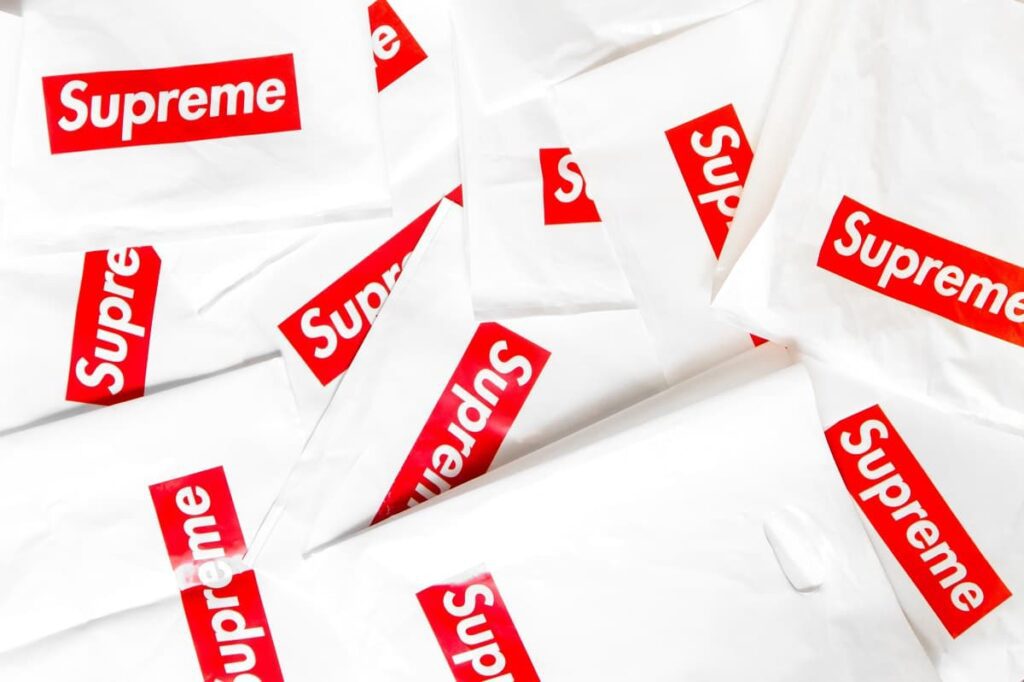
ทำไมต้องใช้ Supreme Font ในแอพมือถือ?
คุณรู้หรือไม่ว่าแบบอักษรสูงสุดนั้นเพิ่มขึ้นอย่างรวดเร็วเมื่อเวลาผ่านไปหลังจากใช้บนโลโก้ บางคนอาจสงสัยว่าทำไมเราควรเลือกใช้แบบอักษรนี้ โดยเฉพาะในแอปบนอุปกรณ์เคลื่อนที่ หรือเราได้ประโยชน์อะไรจากการใช้แบบอักษรนี้ มาพูดถึงบางสิ่งที่บรรยายว่าทำไมฟอนต์นี้ถึงเป็นทอล์คออฟเดอะทาวน์ และคุณต้องลงมือสำหรับโปรเจ็กต์ในอนาคตของคุณ
มันช่วยเพิ่มความสามารถในการอ่าน
สำหรับนักพัฒนาหรือนักออกแบบ ความสามารถในการอ่านเป็นประเด็นหลัก เพราะหากผู้อ่านไม่สามารถเข้าใจมุมมองของคุณได้ ไซต์ของคุณก็ล้มเหลวอย่างใหญ่หลวง แบบอักษร Supreme หรือแบบอักษร Futura ขึ้นชื่อเรื่องคะแนนความสามารถในการอ่าน ความหนาคงที่ของตัวอักษรแต่ละตัวและการออกแบบที่เรียบง่ายทำให้เข้าใจบริบทได้ง่าย
ไม่เพียงแต่ Futura เท่านั้น แต่ทุกเวอร์ชันทำให้ไซต์เข้าใจได้ง่าย ตัวแปร Supreme ใช้ได้ดีสำหรับจุดประสงค์ในการโฆษณาเนื่องจากคุณสมบัติความเข้าใจนี้
เหมาะสำหรับแบรนด์
หากคุณกำลังใช้งานแบรนด์ คุณต้องใช้แบบอักษรที่เหมาะสมเพื่อทำให้ข้อความดูคมชัด เพื่อให้ผู้คนสามารถรู้ว่าแบรนด์นี้เกี่ยวกับอะไรและให้บริการอะไรแก่ลูกค้า เมื่อพูดถึงการสร้างอำนาจแบรนด์ การเลือกแบบอักษรที่เหมาะสมเป็นสิ่งสำคัญ Futura เวอร์ชันนี้มีเส้นขีดบางๆ ที่ทำให้ข้อความดูชัดเจนยิ่งขึ้นด้วยขอบที่แหลมคม นั่นเป็นเหตุผลที่ผู้คนเลือกมันอย่างมากด้วยเหตุนี้
ใช้โดยแบรนด์ใหญ่
คุณรู้หรือไม่ว่าแบรนด์ชั้นนำมากมายใช้ฟอนต์ Futura รุ่นต่างๆ มาหลายปีนี้ ซึ่งได้เพิ่มความโดดเด่นของฟอนต์นี้ ตอนนี้ผู้คนไม่คิดว่าเป็นวินาทีก่อนใช้งานแบบอักษรนี้ ทุกคนเคยใช้โลโก้นี้ในโลโก้ของตน ตั้งแต่ Dominos ไปจนถึง Nike ไปจนถึงแบรนด์อื่นๆ และที่เหลือคือประวัติศาสตร์ กล่าวโดยย่อ ฟอนต์ Futura ไม่ได้เชื่อมโยงกับ Supreme เท่านั้น เนื่องจากมีชื่อที่มีชื่อเสียงอื่นๆ ที่เกี่ยวข้องด้วย
แบบอักษรอเนกประสงค์
อะไรจะดีไปกว่าการใช้แบบอักษรอเนกประสงค์บนเว็บไซต์ของคุณที่มีลายเส้นและการออกแบบแบบอักษรที่แตกต่างกัน นี่คือสิ่งที่ดีที่สุด Futura เวอร์ชันดัดแปลงนี้ใช้งานได้หลากหลายและปรับให้เข้ากับการออกแบบประเภทต่างๆ ได้ค่อนข้างดี สำหรับแอพมือถือต่างๆ คุณสามารถทดลองใช้งานได้อย่างง่ายดายโดยไม่ต้องสงสัย
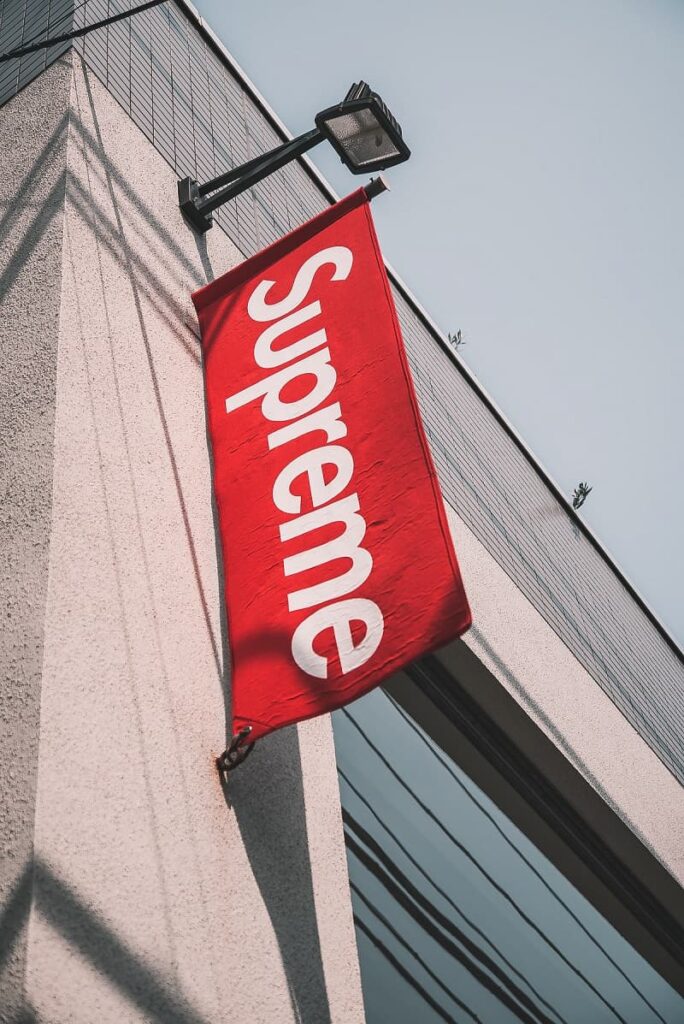
ทางเลือกต่าง ๆ สำหรับ Supreme Font
มีทางเลือกอื่นสำหรับฟอนต์นี้ ซึ่งคุณสามารถคิดได้เช่นกันว่าคุณกำลังจะเปิดตัวแอพมือถือใหม่หรือวางแผนที่จะเริ่มต้นธุรกิจใหม่ แต่ไม่พบฟอนต์ที่ดีที่สุดในเรื่องนี้ แบบอักษรนี้มีทางเลือกสองสามทาง
Didact กอธิคอักษร
เป็นฟอนต์ sans-serif ที่มีการออกแบบมาตรฐานและเรียบง่าย ขออภัย คุณจะไม่พบเวอร์ชันที่เป็นตัวหนา ดังนั้นโปรดรักษาแบบอักษรนี้ให้ปลอดภัยสำหรับรูปแบบมาตรฐานเท่านั้น คุณอาจสังเกตเห็นแบบอักษรประเภทนี้ในชั้นเรียน แต่สามารถเผยแพร่บนกระดานได้อย่างรวดเร็ว ในทางกลับกัน มันเป็นหนึ่งในทางเลือกที่ยอดเยี่ยมสำหรับฟอนต์ Supreme ที่ทุกคนชื่นชอบ
แบบอักษร Poppins
นี่เป็นอีกทางเลือกหนึ่งที่เป็น sans-serif ด้วย ความหนาของแบบอักษรนี้ค่อนข้างบาง ในขณะที่ความกว้างก็เล็กเช่นกัน น่าแปลกที่คุณจะได้ตัวละครมากมายในภาษาเนปาลและอินเดีย ตัวพิมพ์ใหญ่ของแบบอักษรนี้มีความยาวและความสูงเท่ากัน ความแตกต่างเพียงอย่างเดียวที่คุณจะพบระหว่างแบบอักษร Poppin และ Supreme คือระดับความหนา
แบบอักษร Nunito Sans
เมื่อพูดถึงความหนา มันค่อนข้างคล้ายกับฟอนต์ Poppin แต่นอกเหนือจากนั้น คุณจะไม่พบความแตกต่างที่สำคัญระหว่างฟอนต์ Numito และ Supreme แบบอักษร sans-serif ทั้งสองแบบสามารถใช้ในโครงการต่างๆ ได้ ประกอบด้วยสองเวอร์ชันที่แตกต่างกัน ดังนั้นคุณสามารถเลือกได้ตามความต้องการ คุณสามารถรับอักขระละตินหลักทั้งหมดในแบบอักษรนี้
แบบอักษร ITC Avant Garde Gothic
มาพูดถึงทางเลือกสุดท้ายกัน ซึ่งก็คือ ITC Avant Garde Gothic ซานเซอริฟนี้สร้างกระแสมาตั้งแต่ปี 1970 และทุกวันนี้ไม่มีใครถามได้ว่าทำไมคุณถึงควรคำนึงถึงมัน นอกจากนี้ยังมาพร้อมกับเวอร์ชันต่างๆ มากมาย คุณจึงมีตัวเลือกต่างๆ ให้เลือกใช้ ตั้งแต่โลโก้อัลเบอร์ตาไปจนถึงซีรีย์ดราม่ายอดนิยมของ Netflix แบบอักษรนี้ถูกใช้ทุกที่
โลโก้อักษรอักษรเครื่องหมายการค้า
บริษัทที่มีอำนาจสูงสุดต้องดิ้นรนอย่างมากเพื่อจะได้เครื่องหมายการค้าโลโก้ของแบรนด์ ไม่ใช่แค่โลโก้เท่านั้น แต่พวกเขายังต้องทำงานหนักกับคำอธิบายด้วย เมื่อหลายปีก่อน พวกเขาพบกับข้อขัดแย้งต่างๆ รวมถึงการไม่มีตัวอักษรที่ชัดเจนในแบบอักษร การต่อสู้ทางกฎหมายเกิดขึ้นหลายครั้ง และในท้ายที่สุด พวกเขาก็สามารถได้รับเครื่องหมายการค้าโลโก้ของตน
คู่มือนี้เกี่ยวกับ Supreme Font เหตุใดคุณจึงควรใช้ และทางเลือกอื่นทั่วไป กล่าวโดยย่อ คุณจะพบรายละเอียดทั้งหมดของฟอนต์นี้ ซึ่งจะเป็นประโยชน์หากคุณตั้งตารอที่จะใช้มันในโปรเจ็กต์ถัดไปของคุณ มีแบรนด์และชื่อใหญ่มากมายกระจายอยู่ทั่วโลกที่ใช้แบบอักษรที่ยอดเยี่ยมและเป็นที่นิยมในการออกแบบของพวกเขา ดังนั้นฉันมั่นใจว่าคุณจะไม่พลาดโอกาสนี้เช่นกัน
ฟอนต์ Futura หลากหลายรูปแบบที่น่าทึ่งนี้คือทั้งหมดที่คุณต้องการสำหรับโครงการที่ประสบความสำเร็จ ฉันหวังว่าบทความนี้จะแนะนำคุณเพียงพอเพื่อให้คุณสามารถตัดสินใจว่าจะเลือกใช้หรือไม่